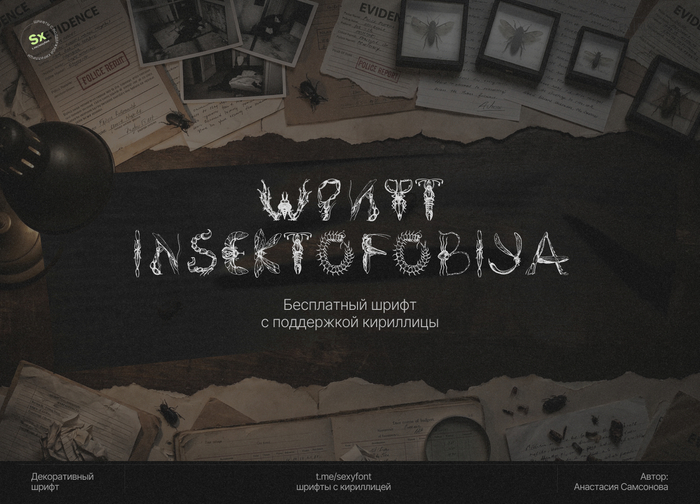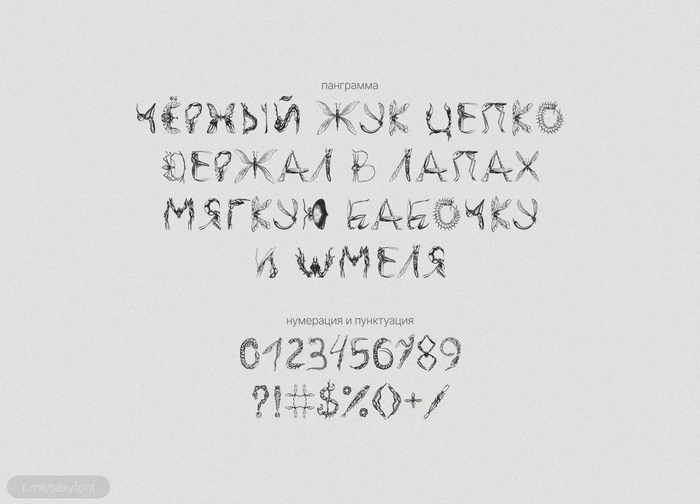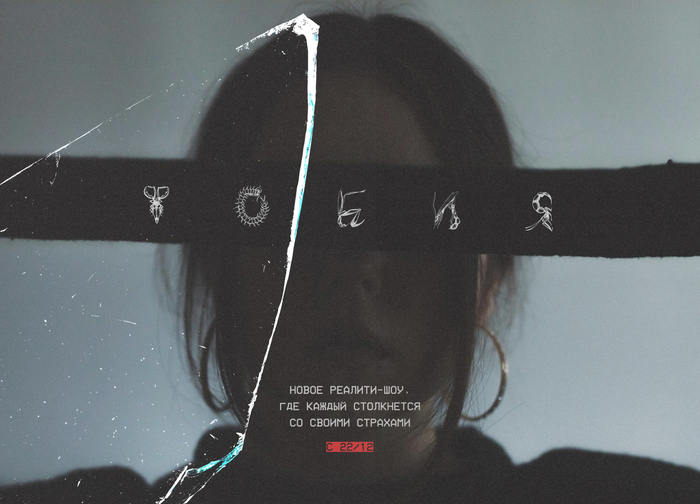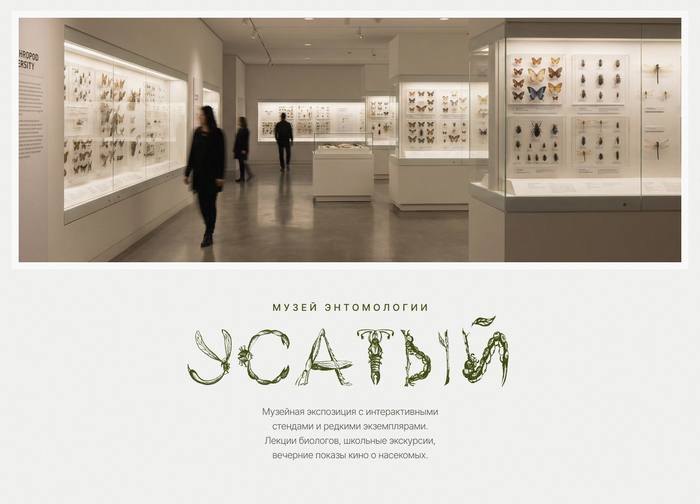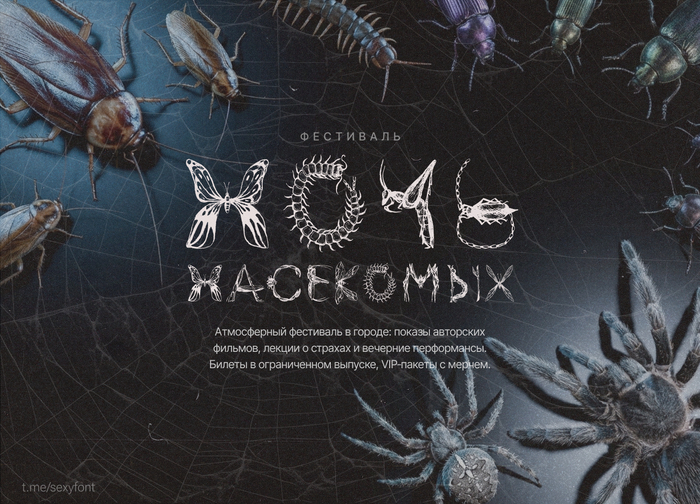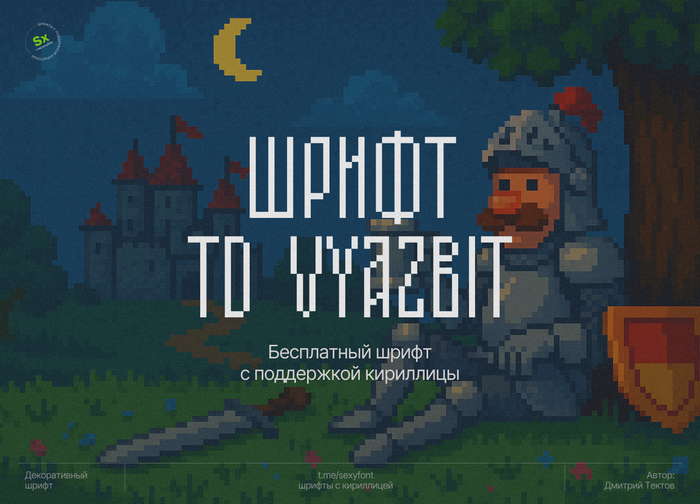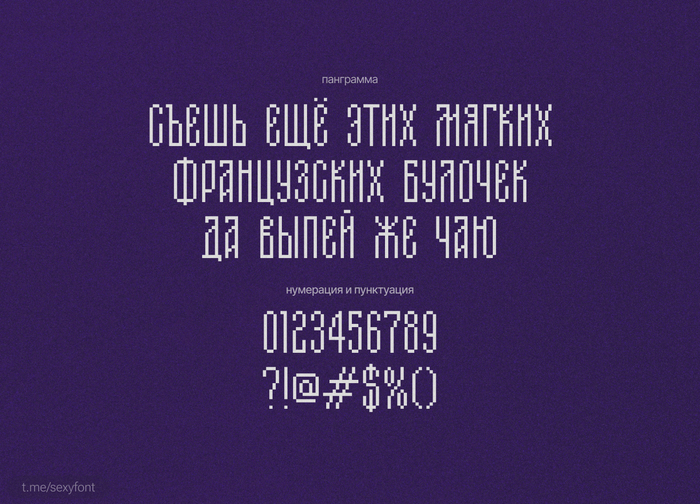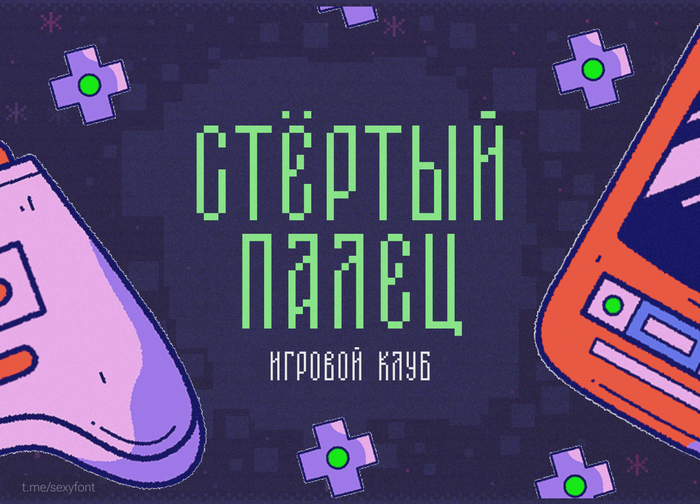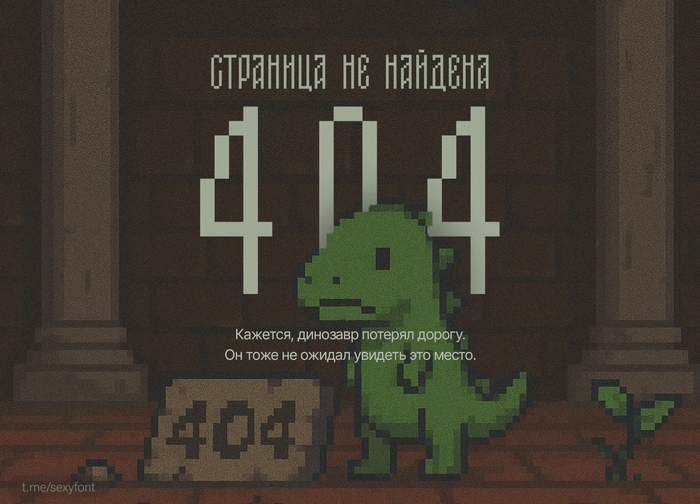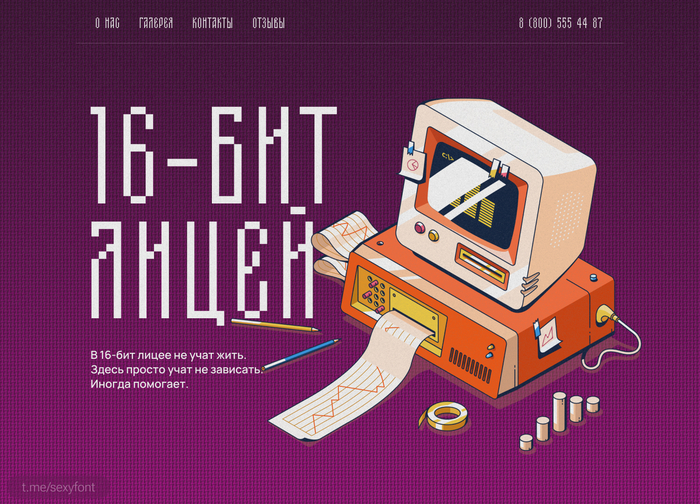
Шрифт Insektofobiya
Insektofobiya. Шрифт для тех, кто хочет, чтобы текст ползал 🪳Буквально. Каждая буква сделана из жуков, пауков и прочих товарищей с шестью лапами. Бесплатный, есть кириллица, вызывает лёгкую панику у людей со слабыми нервами.Идеален для хоррор-постеров, обложек книг и пугания дизайнеров с энтомофобией.Автор: Анастасия Самсонова (спасибо, что создала это)
Бесплатный Шрифт ST-Africa
Продолжаю собирать кириллицу. Шрифт ST-Africa. Шрифт наследие советских агитационных плакатов посвящённых борьбе африканских народов с колониализмом.
Ярко выраженная акциденция, крупные, резкие формы.
Автор: Александр Шиманов Александр "STAN" Шиманов
Подборочка бесплатных брутальных шрифтов
Подборочка брутальных шрифтов. Такую вот презенташку сварганил на днях.
Шрифт Tovar. Бесплатная кириллица
Шрифт Tovar. Плотный, жирный шрифт для твоих проектов) Полность бесплатный для личного и коммерции.Автор: Ilya Kolobov
Шрифт TD Vyazbit
Новая презентация и шрифт. TD Vyazbit. Пиксельный шрифт для коротких заголовков) В идеале 1-2 слова. Иначе читаемость пропадает полностью.
Автор: Дмитрий Тектов
Бесплатный шрифт Dygyn
Дыгын - акидентная антика с северной душой. Шрифт, созданный на основе орнаментов народа саха.От автора: Шрифт, рождённый из орнаментов народа саха, веками передававшихся из уст в узор. В якутской мифологии слово «дыгын» означает «молния» символ мощи и стремительности, придающий слову особую энергию.Автор: Нана Колодезникова
Бесплатный шрифт Bim «Большая Ивановская Мануфактура»
Шрифт Bim или «Большая Ивановская Мануфактура».Заценил его: читается легко, кое-где напоминает Soyuz, но без ощущения, что его уже юзали все дизайнеры на районе. Есть прикольные нестандартные символы, а ещё он абсолютно бесплатный — и для личных, и для коммерческих дел.Автор: Ilya Kolobov